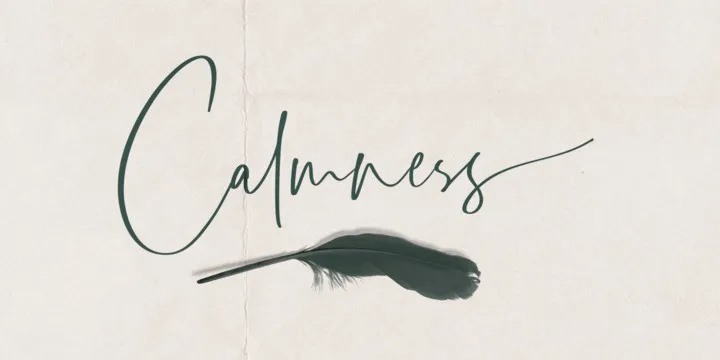
Barrington Calligraphy Font – Download Grátis
Estamos muito felizes por apresentar a Barrington Calligraphy Font para vocês! Esta elegante fonte é perfeita para projetos de marca e logotipo, embalagens de produtos, títulos nas capas de livros ou revistas, até mesmo estilizados para cartões de visita. Ela foi criada pelo designer Hamilton, apresentando uma combinação única entre a calligrafia casual e o estilo do desenho manual. A Barrington possui 64 ligaturas que fornecem um aspecto natural à fonte, alternativas maiúsculas para dar diferentes estilos ao texto, e até mesmo suporta final swash. Esta font é ideal tanto para criações de marca profissionais quanto para adicionar um toque personalizado a qualquer projeto visual. Essa font oferece a liberdade de expressar-se em uma linguagem elegante e acessível ao mesmo tempo. Se você está buscando uma fonte que vai além da simples escolha, a Barrington é sua escolha perfeita para criar designs únicos e memoráveis. A Barrington pode ser o grampo perfeito adicionado à sua biblioteca de fonts favoritas!